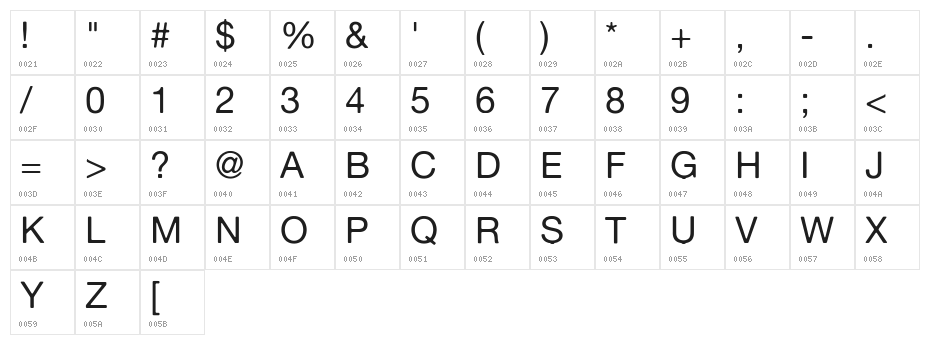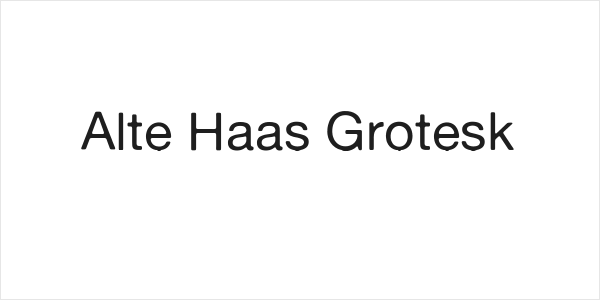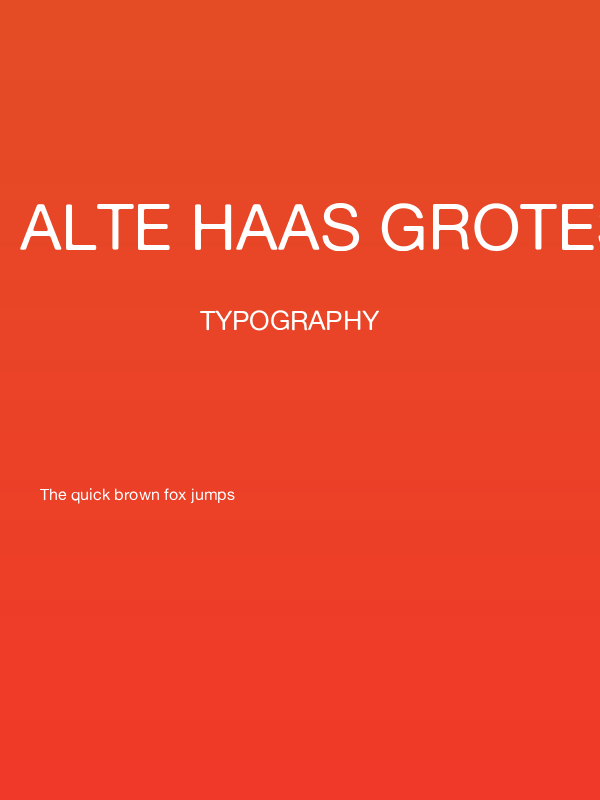
Alte Haas Grotesk Font
| Projets proposés | Ideal for branding, web design, editorial layouts, and corporate materials due to its clarity and modern appeal. |